Top 10 xu hướng font chữ hot nhất trong thiết kế đồ họa năm 2022
Kiểu chữ là một yếu tố quan trọng như vậy trong thiết kế và truyền thông nói chung. Bởi vì không chỉ là thông điệp thực tế mới có vai trò quan trọng trong việc truyền tải một thông điệp nào đó, mà còn phải suy nghĩ về loại phong cách mà thông điệp đó được thực hiện. Trong cùng một văn bản thuần túy có thể đưa ra một thông điệp hoàn toàn khác khi nó được đặt bằng phông chữ khác nhau. Vì vậy bạn cần lưu ý để chọn kiểu phông chữ một cách khôn ngoan và xác định đâu là kiểu chữ phù hợp nhất cho thương hiệu hoặc thiết kế của bạn. Bài viết là một số font chữ hot nhất trong thiết kế đồ họa 2022. Hãy cùng Top Share tìm hiểu nhé!
Retro Fonts
Trong cuộc sống hiện đại với nhịp sống nhanh và hối hả, con người lại càng có xu hướng hồi tưởng quá khứ thông qua những tác phẩm nghệ thuật. Để đáp ứng thị hiếu của đông đảo người tiêu dùng, hàng loạt cách mặt hàng, dịch vụ mang âm hưởng cổ điển được tung ra thị trường. Bởi vậy, những người thiết kế đã nhanh chóng bắt kịp xu thế để đưa ra các sản phẩm mang đậm phong cách Retro gợi nhớ cho khách hàng về những hoài niệm thoáng qua trong nhịp sống hiện đại.
Phong cách thiết kế nhà ở retro (retrospective) bắt nguồn từ Bắc Âu vào những năm 50 và đã mang đến sự thay đổi trên toàn thế giới. Những tư tưởng hiện đại cấp tiến đã làm thay đổi phong cách thiết kế. Phong cách trang trí nội thất retro trong thập kỉ này dựa trên những nguyên tắc thiết kế cổ điển vậy nên trông nó có nét giống với phong cách thiết kế ngày nay.
Phong cách retro thịnh hành vào những năm 1950 – 1970, nó mang những giá trị hoài cổ, cổ điển xinh đẹp và dịu dàng. Phong cách retro biểu hiện cho sự chân thành, đơn giản, nhưng hiện đại và quyến rũ trong cuộc sống hiện đại. Có thể nói rằng, retro là một phong cách mang tính chất hoài cổ nhưng cũng không kém phần hiện đại.
Phong cách retro là biểu hiện cho sự sang trọng, sành điệu và thời thượng, nét quyến rũ của nó được tạo nên từ vẻ quý tộc trong sự hoài cổ và nét hoang dại của thiên nhiên. Vì vậy, màu sắc chủ đạo trong phong cách này là các tone màu nâu đỏ, cam ngọt, xanh lam,… kết hợp với các màu đậm và nổi bật như xanh non, vàng đậm,…
Svelte Serifs
'Svelte Serifs'Nó bao gồm các kiểu dáng thẳng đứng từ Regular đến ExtraBold. Phù hợp cho hiển thị, văn bản ngắn và sắp chữ xếp chồng. Nó chứa 394 glyphs với phạm vi ngôn ngữ latin rộng rãi. Serifs hiện đang được sử dụng rộng rãi ở dạng mỏng hơn, nó mang lại một cái nhìn tinh vi hơn một chút. Chúng được sử dụng rất nhiều khi kết hợp với chụp ảnh theo phong cách cổ điển với những kỹ thuật ánh sáng tinh tế và kết cấu hạt. Kết hợp với hình minh họa nhân vật hiện đại, tươi mới, nhãn hiệu may mặc sáng tạo hoặc bao bì hiện đại 'lấy cảm hứng từ retro'.
Modern Geometric Sans
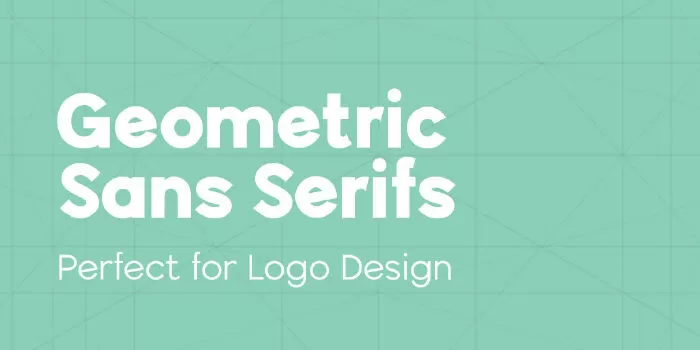
Sans Serifs đã trở thành lựa chọn 'cơ bản' cho các nhà thiết kế và mọi người nói chung trong những thập kỷ qua. Để tránh một mẫu thiết kế quá 'cổ điển' hoặc 'nhàm chán', bạn có thể nhúng vào Arial hoặc Helvetica. Mặc dù đây là những phông chữ tốt về mặt thiết kế, các nhà thiết kế đã tìm kiếm những cách khác để sử dụng Sans nhưng thêm nhiều ký tự hơn. Nó có thể thân thiện hơn, nó có thể là kỹ thuật và chắc chắn hơn.
Trong các kiểu chữ Geometric Sans hiện đại, có rất nhiều hướng khác nhau để đi đến vì vậy bạn phải quyết định cách tốt nhất cho thiết kế của mình và với kiểu chữ phổ biến này, bạn chắc chắn sẽ tìm thấy sự phù hợp hoàn hảo của mình.
Expressive Display Fonts
kiểu chữ không phải lúc nào cũng có mục đích chính là dễ đọc trong vòng một giây. Một số thiết kế cho phép chúng tôi biểu đạt và thử nghiệm hơn một chút về các mẫu chữ mà chúng tôi đang sử dụng với tư cách là nhà thiết kế. Và với rất nhiều nhà thiết kế kiểu chữ đã tạo ra những kiểu chữ 'on-the-edge' đáng kinh ngạc cho phép chúng tôi làm việc với một phông chữ có thể cài đặt mà không cần phải tạo mọi thứ bằng tay. Hoàn toàn một trong những ưu điểm của phần mềm tạo phông chữ có thể truy cập được cho nhiều đối tượng hơn là số lượng lớn các tùy chọn có sẵn cho các kiểu thử nghiệm này.
Loopy
Kiểu phông chữ này có tác dụng nhân bản nhất định đối với thiết kế của bạn bằng cách thêm các đường cong bất ngờ ở đây và ở đó hoặc bằng cách tạo ra một dấu hiệu hoàn toàn được tạo ra từ các hướng hữu cơ của các dạng chữ cái. Nó mang lại cảm giác vui tươi, dễ tiếp cận và dễ gần cho thiết kế của bạn và nhiều thương hiệu đã chọn hướng đi này trong những năm qua và nó ngày càng phổ biến hơn.
Kiểu phông chữ này cũng có nhiều mức độ đậm nhạt về số lượng đường cong và sửa đổi, vì vậy hãy lựa chọn một cách khôn ngoan những gì phù hợp nhất cho thương hiệu của bạn. Bạn có thể chọn một phông chữ chỉ có đuôi cong, độc đáo ở phần đuôi của chữ 'j' viết thường hoặc một phông chữ hoàn toàn.